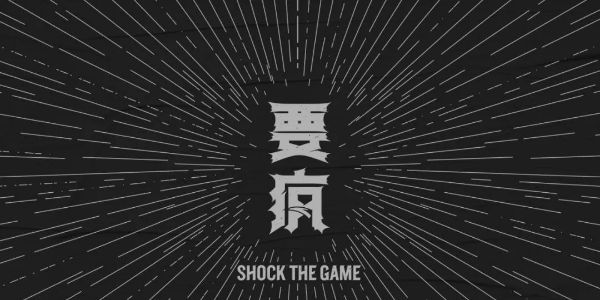
汉仪瑞兽字体介绍,从“山海经”里走出来的字体
汉仪瑞兽 | 整体特点
“汉仪瑞兽”是一款兼具书写感与力量感,冲击力强,个性张扬的非传统楷体味道的标题美术字。这款字既保留传统书写韵味,又打破旧有楷书的印象,诠释新潮流下的复古感。字体在笔画终端上做了一些几何图形化的处理,像是兽爪的尖锐形状装饰,笔画粗壮,点顿有力,笔画富有弹性。
汉仪瑞兽 | 字形特点
“汉仪瑞兽”的字形方正,布白合理,粗细灰度均匀。字面、横纵向重心稳定一致。笔画多为向下且外扩的走势,撇捺浑厚,字形上略有上收下放之势。
汉仪瑞兽 | 笔画特点
“汉仪瑞兽”结构上左边略紧、右边舒展宽松。起笔、收笔和转折处都有顿笔,笔画有书写的温度。横画向右上倾斜,有速度感。
笔画终端做了几何图形化的处理,终端装饰能联想到尖锐的兽爪和獠牙。
不同位置的横画在笔画粗细、角度和终端装饰上有差异。竖画在空间充足时用钩笔竖和顿笔竖,空间不足时简化竖的细节。
撇画丰富多样。长撇线条饱满有弹性。短撇的装饰性起笔收笔在空间拥挤的结构中得到简化,与点画对称使用的短撇跟点画设计元素更接近。平撇简洁,弱化装饰性终端。
不同位置的点画在终端的装饰和笔画走势上也有各自的特征和差异。
横钩、弯钩、戈钩、竖弯钩、卧钩、横折钩、竖勾在终端的装饰各有不同。
汉仪瑞兽 | 中西文匹配
“汉仪瑞兽”的西文为粗壮的衬线字体。小写字母字高大,升部降部短,与中文设计中方正的字形风格更一致,搭配和谐。
“汉仪瑞兽”的西文笔画模仿中文设计特征,略带倾斜角度,使字形呈梯形,稳定有气势。西文每笔都带有内凹的弧线,增加西文的动感,既符合传统西文审美,又平衡了汉字笔画向右上倾斜带来的动势。
西文中的衬线是“附加在一个笔画的末端的一条线或是一笔”。通常情况下衬线的装饰效果不会过度影响字形。然而在某些特殊的字体里,衬线除了装饰作用,也在向结构功能性延伸。比如在美国19世纪中叶十分流行的 American Tuscan 风格木活字。
汉仪瑞兽的西文借鉴了木活字的特征,精致的弧线重现了雕刻感。与中文设计中笔画的雕刻感相呼应。
大写字母衬线角度大,能减少字谷的空白空间。大写字母衬线切去了小写字母的尖角,与其他大写字母更统一,风格浑厚复古。 大小写字母终端细微处都处理成弧线,更灵动精致。
修正“X”视错觉;第二笔调整的更细,入笔有西文书法的韵味,与中文的书写感相匹配。如果“X”只是简单死板的对称,两笔画大面积交叉,带来笔画断开不连续的视错觉,字母下部分显得小而且重心低。
“汉仪瑞兽”除了常见的等高数字外,还设计了一组老式数字,去配合它的文化韵味和使用场景。
汉仪瑞兽 | 字体样张